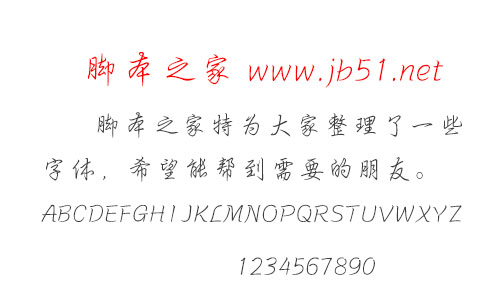
方正行楷硬筆字體是方正字庫(kù)推出的一款藝術(shù)字體,行楷細(xì)是照著任政的楷書(shū)用硬筆臨摹的楷體,筆畫(huà)筆順筆鋒均延續(xù)了原書(shū)法的特征,線條均勻細(xì)瘦,圓轉(zhuǎn)流暢,淡雅清新。用較細(xì)線條書(shū)寫(xiě)楷書(shū),筆畫(huà)柔韌挺拔似蘭葉臨風(fēng)搖曳,飄逸自如。 轉(zhuǎn)折處輕提暗過(guò),遒勁而圓活;筆畫(huà)間頓挫映帶之妙;每一筆都力求生動(dòng)活潑,無(wú)一筆平鋪而直過(guò)。適用于排版的小字,歡迎喜歡方正行楷硬筆字體的朋友前來(lái)下載使用。